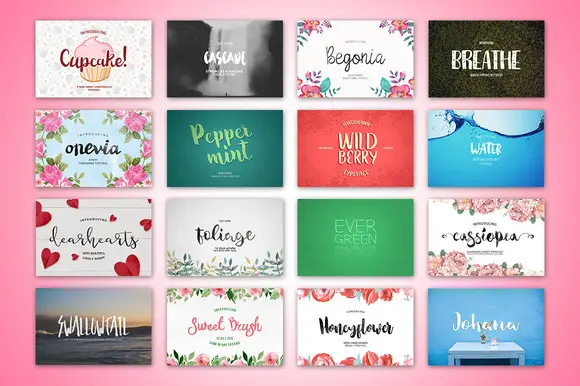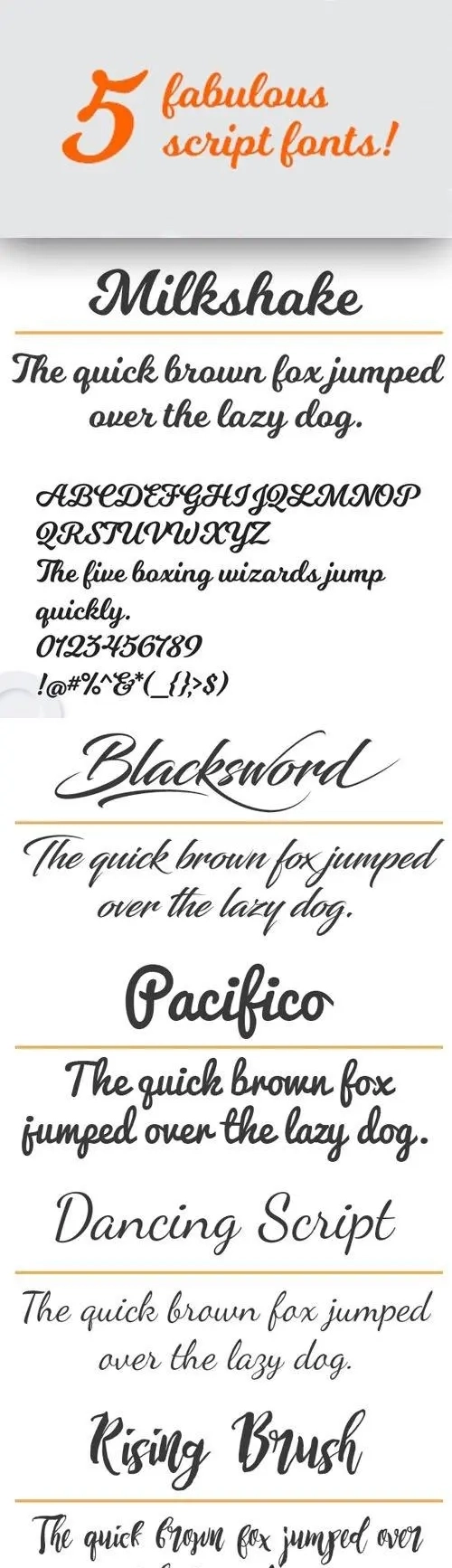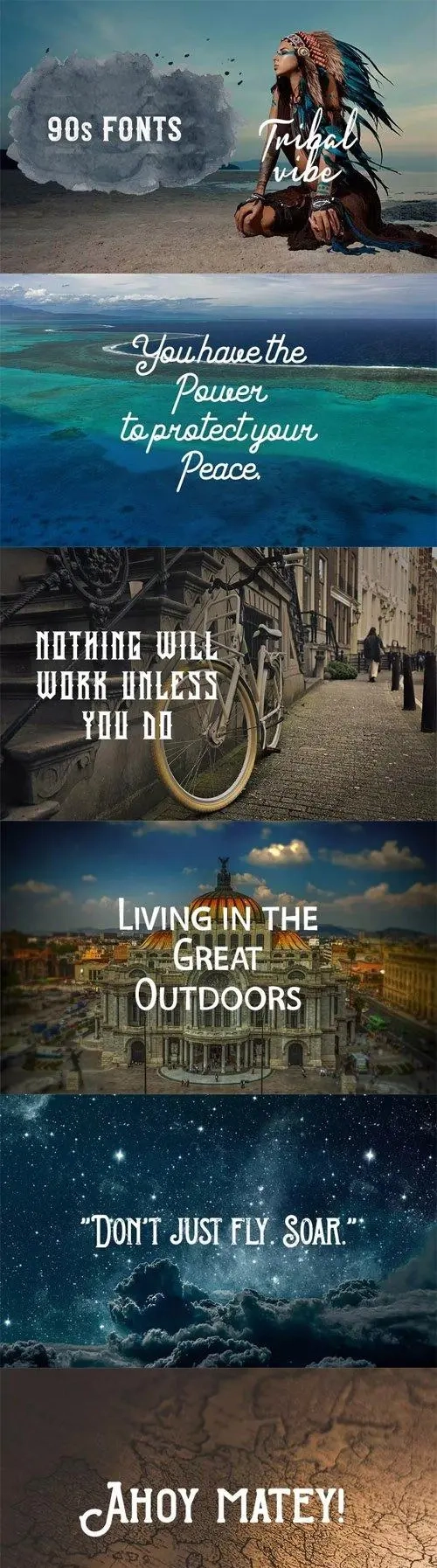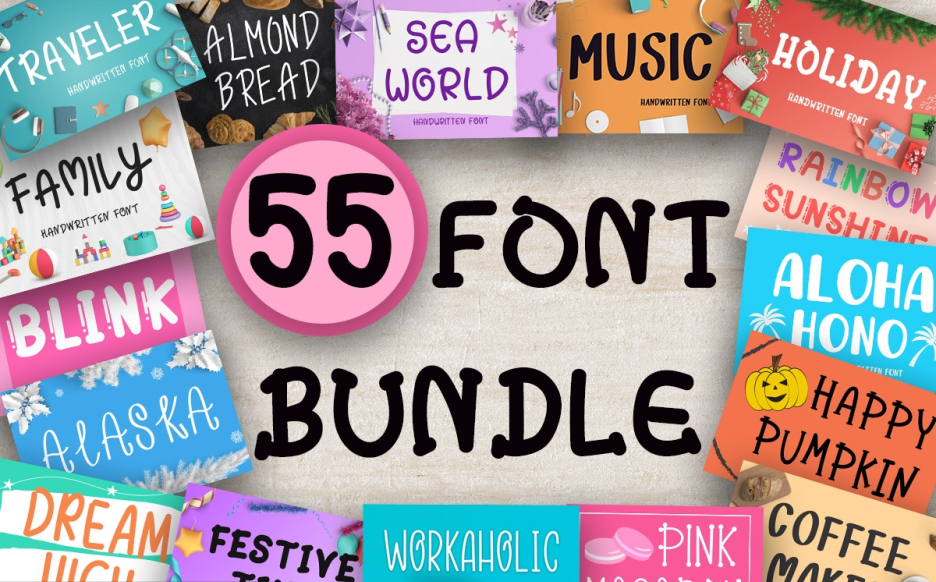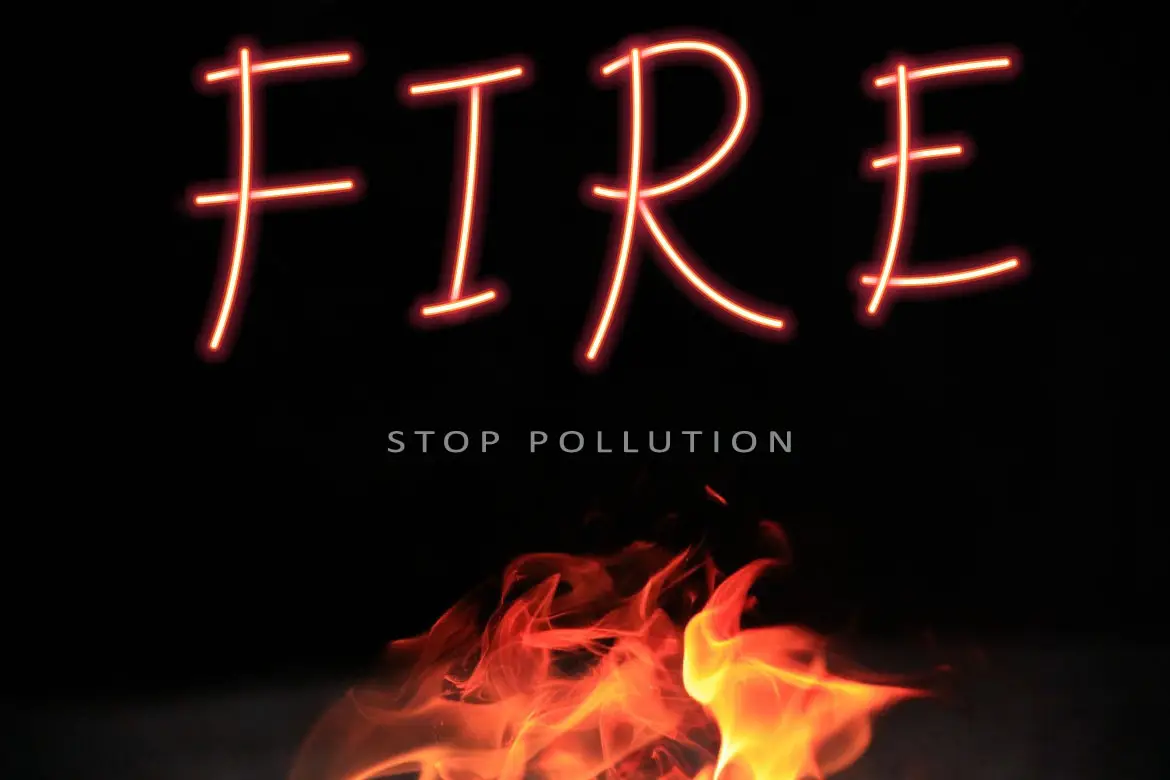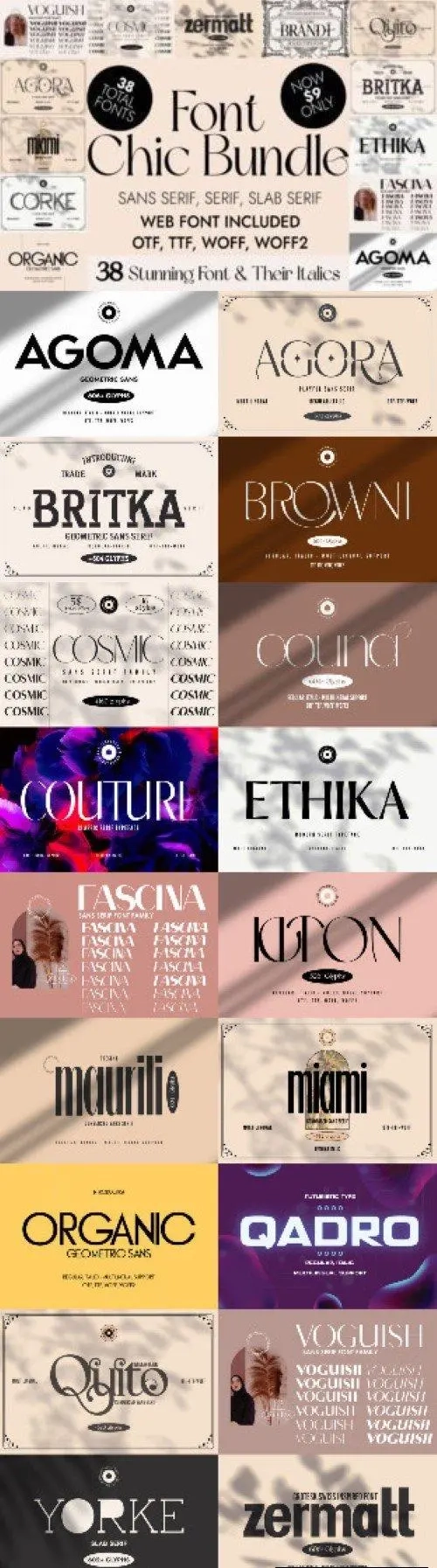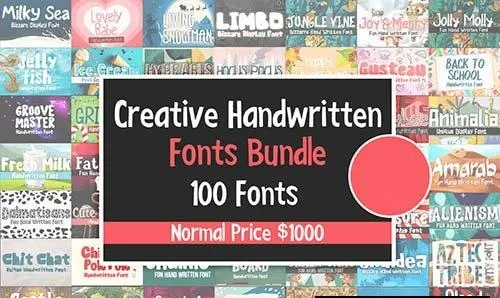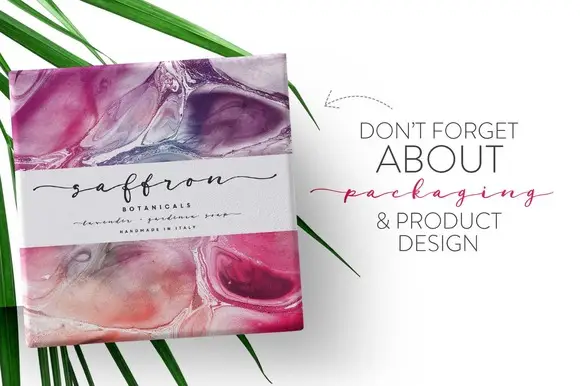
嘿,创意灵魂!🎨✨ 准备好提升你的设计水平了吗?无论你是经验丰富的平面设计师,还是刚刚踏上字体设计之旅的新手,拥有合适的字体往往能决定项目的成败。我为你整理出了终极画笔包合集 第163部分——一个藏有20款惊艳字体套装、图案合集和手写笔触包的宝库,能让你的作品瞬间增添独特魅力。快来一探究竟,找到你下一个最爱的字型吧!🚀
为什么要使用这些字体套装?
字体是设计的灵魂。它们奠定基调、讲述故事,还能将平淡的布局转变为视觉杰作。🖌️ 通过这些精心策划的字体包,你可以一次性获得多样性、高品质和多用途性。无论你是在打造奢侈品牌形象、制作有趣的社交媒体帖子,还是设计怀旧复古海报,这些字体包都能满足你的需求。
精选20大字体包推荐
字体 + 图案组合包
字体与图案双倍乐趣!🎉 这个精心挑选的合集为你提供了多种字体样式和粗细,以及华丽的图案——非常适合品牌设计、包装和壁纸。快来入手,让你的设计焕发生机吧!✨
5款精美手写字体包
五款华丽的手写字体,尽显优雅!🖋️ 完美适用于婚礼请柬、标志设计和品牌塑造——这些流畅的字体风格带来个性化、手工制作的触感。您一定会爱上这些花饰和连笔!😍
32款字体合集
一个包含32款字体的超大合集,涵盖衬线体、无衬线体、手写体和展示体!🎯 这是你实现多样化的不二之选。无论你需要经典还是独特风格,每个项目都能找到完美匹配。超值不容错过!💥
字体套装2
这里的核心就是多样性!🎨 从优雅的衬线字体、现代无衬线字体到俏皮的手写体,这个捆绑包覆盖了所有风格。无论是网页还是印刷品都非常适合——是快速扩充你的字体库的理想选择!🚀
30款字体包 [2022年9月]
精选30种多样化字体风格!🌟 这套字体包汇集了衬线体、无衬线体、手写体和展示字体,堪称宝藏合集。多种字重赋予你极大的灵活性——立即入手,瞬间升级你的设计工具箱!🔥
全能字体套装包
这个字体包真的应有尽有!🎁 手写体、无衬线体、展示体——并提供 OTF、TTF 和 WOFF 格式。无论你在做什么项目,都能为你的设计找到完美的风格。每一位创意专业人士的必备之选!💪
32款字体包
又一套令人惊叹的32款字体合集!🎉 这次主打多样化,涵盖优雅衬线体和现代无衬线体。非常适合那些喜欢随手拥有多种字重和样式的人。设计、重复、创作!🌀
90年代字体包
超级酷炫!🛹✨ 用大胆、俏皮且怀旧的字体带回90年代。非常适合复古品牌设计、专辑封面或怀旧社交媒体帖子。保证带来复古潮流感受!🎶
未来感字体包
凭借时尚、前沿的字体抢占先机!🤖 该字体包主打现代美学——无衬线字体和粗体展示字体,尽显创新风范。非常适合科技品牌、应用及科幻项目。🚀
字体图形包
设计师梦寐以求的手写体、展示体与无衬线字体的完美组合!🖍️ 多种字重,助你在版式中打造优美的层级结构。这款百搭字体系列适用于从标志设计到编辑排版的各类场景。📰
时尚、奢华与优雅字体系列
增添一份优雅气质!💎 这套字体尽显精致——衬线、无衬线以及手写字体,奢华感十足。非常适合高端品牌标识、婚礼请柬和高级包装。香奈儿般的高级感,有人要吗?👜
大型字体套装1
要么做大,要么回家!📏 这款合集汇集了醒目、有力的字体,绝对吸引眼球。从现代无衬线体到优雅衬线体,这些字体的设计让您的标题令人过目不忘。🔥
精彩字体包 – 50款字体
50款独特字体?没错,就是它!🎉 这套字体包汇集了衬线体、无衬线体等大量字体,每一款都经过精心打磨,随时可用。你再也不用担心灵感枯竭了!🌟
大促31号字体
以超值价格抢购这款醒目、动感的字体!💰 完美适用于标题、海报和品牌设计——清晰易读,彰显个性。多种字重意味着你可以在任何场景使用它。🏷️
画笔字体合集
获得那种手工质感、墨迹风格的效果!🖌️ 这套画笔字体集合为任意项目增添有机纹理与个性,非常适合引语、品牌设计和街头风格创作。既真实又充满艺术气息!🎨
大型字体合集 3
又一个强大的字体包!💥 包含粗体无衬线字体、优雅的衬线字体以及俏皮的手写字体——这套字体包将为您带来多样化、高质量的设计体验。多种字重供您尽情尝试!🎪
大型字体包
海量选择,包含OTF、TTF和WOFF格式!🌐 这套字体包涵盖衬线、无衬线、展示和手写字体。为设计师的硬盘提供完整的字体排版解决方案!🗂️
创意手写字体包
用手写字体增添一份个性化的人情味!✍️ 这个字体系列包含丰富的草书和展示字体选项,仿佛专为你量身绘制。非常适合卡片、日记和品牌设计。💌
创意字体包
释放你的创造力!🧠 本套装精心融合了衬线体、无衬线体、手写体和展示字体。无论你需要优雅还是现代的风格,这套收藏都能为每一种心情找到完美搭配。🎶
巧手圣诞字体系列
融入节日氛围吧!🎄🎅 这个节日套装包含俏皮手写体和醒目的展示字体,非常适合制作圣诞贺卡、季节性品牌设计和温馨的DIY项目。呵呵呵,您的设计将大放异彩!✨
总结
呼,这真是一场创意之旅!🎢 我们探索了来自 brushespack 系列第163期的20个精彩字体套装——每一个都为您的设计工具箱带来独特之处。从优雅的手写体到未来感的无衬线字体以及节日圣诞字体,总有适合您下一个项目的完美字体。别等了,这些套装很快就会被抢购一空!🏃♂️💨